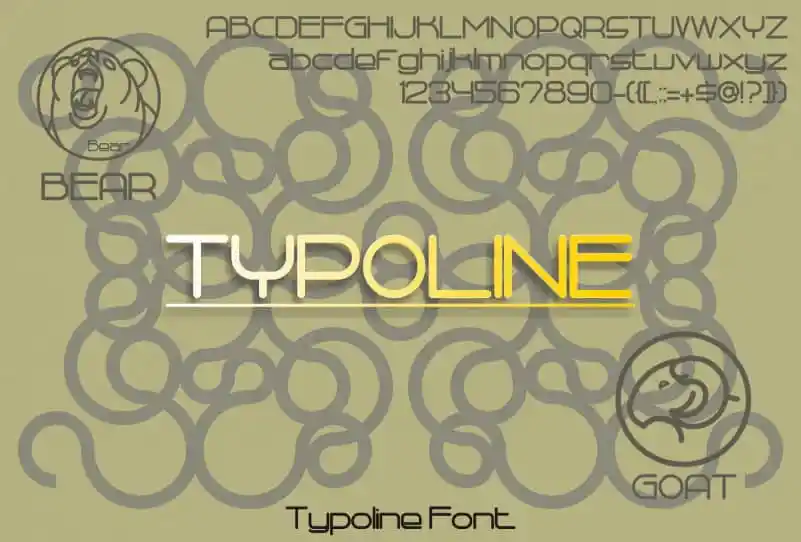
Typoline Sans Serif Font – Download Grátis
A Typoline Sans Serif Font é uma elegante tipografia sans-serif que traz características únicas de linhas redondas, tornando-a fácil de reconhecer para seus leitores. Esta fonte moderna pode ser usada em diversas finalidades como texto impresso, cabeçalhos e texto do corpo na web design, setes tipográficos para marca corporativa, tipoface para anúncios, títulos ou texto para revistas, design de produtos e qualquer embalagem ou etiquetas. A Typoline Sans Serif é uma fonte que se destaca por sua facilidade de leitura e versatilidade em uma variedade de mídias digitais, tornando-a ideal tanto para designers profissionais quanto iniciantes.